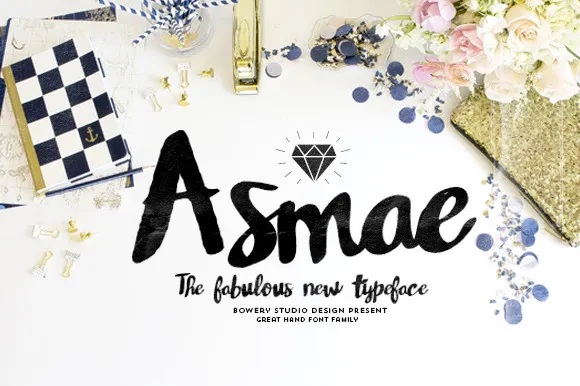
Asmae Handwritten Font – Download Grátis
Asmae é uma fonte escrita à mão criada pelo dedo e caneta, adequada para simular efeitos de escrever a mão nas criações digitais. Perfeita para projetos como cartões de convite, cartas pessoais, selinhos, anúncios, fliers ou até mesmo panfletos. A Asmae traz um toque de leveza e criatividade que torna qualquer projeto uma peça única. Seja para eventos especiais como casamentos ou simples cartões de saudação, a Asmae é certamente o elemento diferenciador que você precisa. Inspirada na natureza delicada das escritas à mão, esta fonte oferece um toque único e encantador às suas criações digitais.